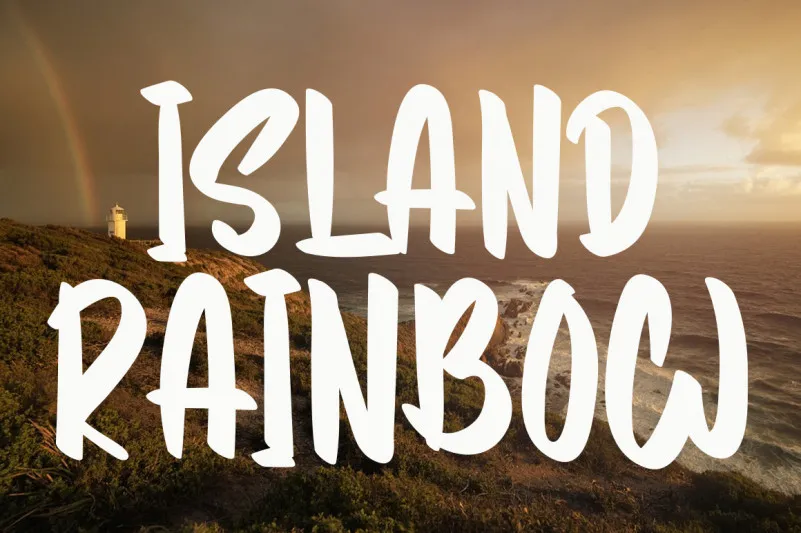
Island Rainbow Font – Fonte Grátis
Island Rainbow Font
A Island Rainbow Font é uma elegante escolha para designers que buscam um script casual e confiável. Esta fonte escrita à mão apresenta um estilo levemente agressivo, garantindo um toque único e inovador sem perder o charme pessoal. Independente do tipo de projeto ou tópico a ser abordado, esta font se destaca pela sua versatilidade, tornando-se uma invaluable adição à coleção de suas fontes. Ela é especialmente adequada para criar uma identidade visual forte e impactante em criações como cartões de visita, selos ou materiais publicitários. Com a Island Rainbow Font da LevinCreative, seu design terá um toque único que tornará qualquer projeto especial.